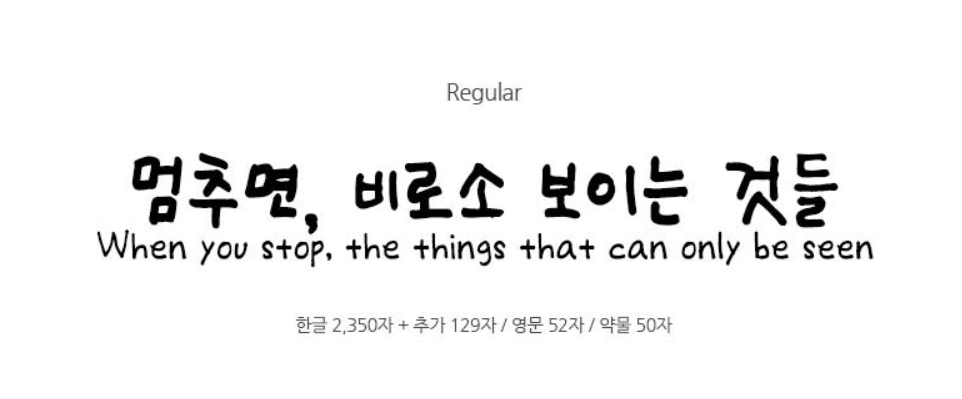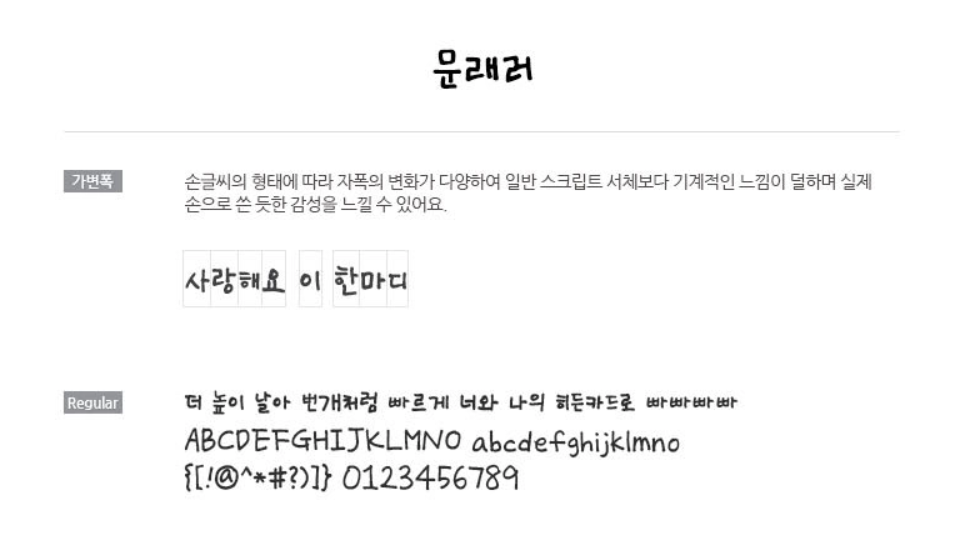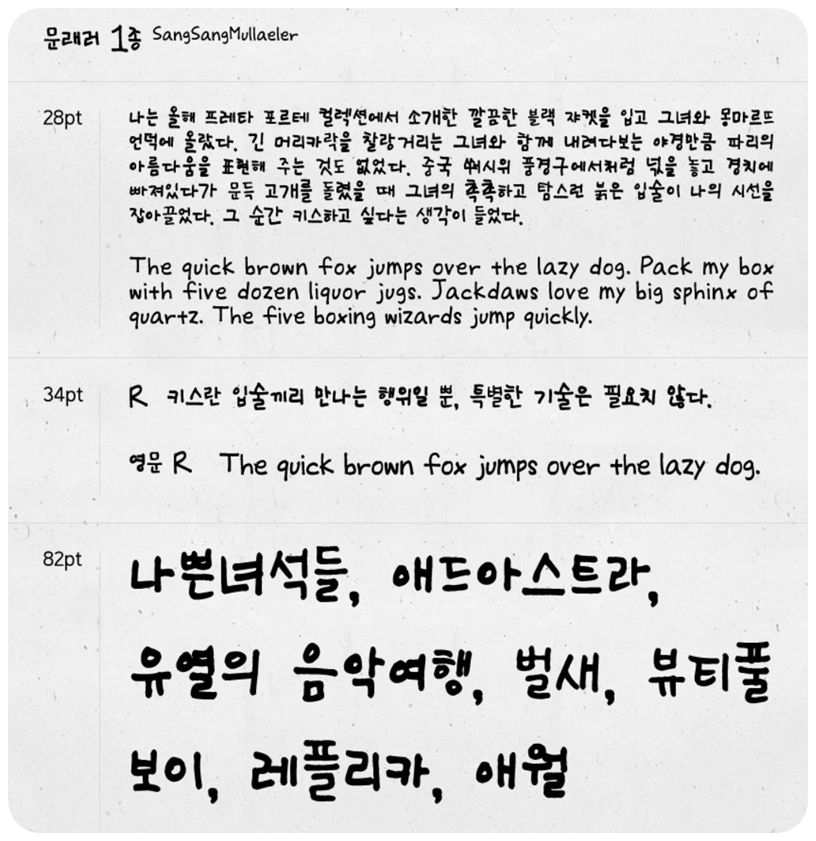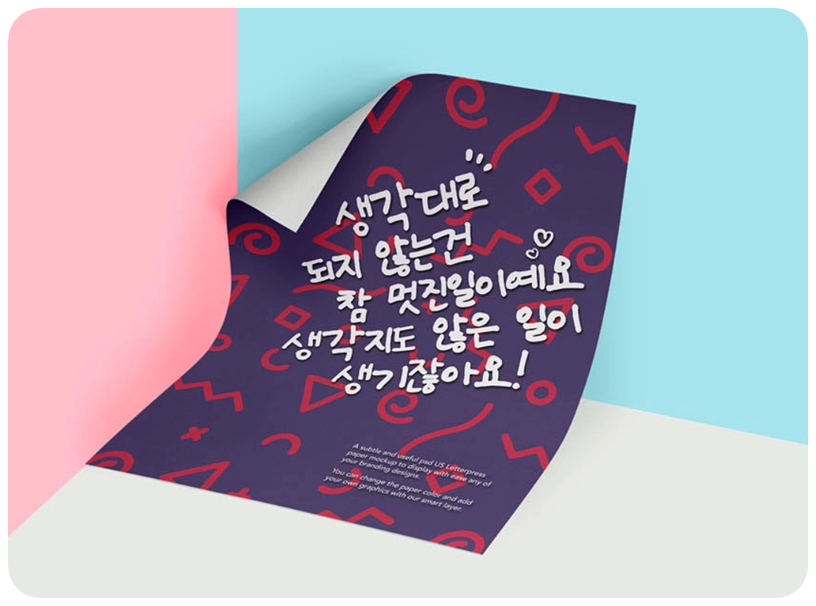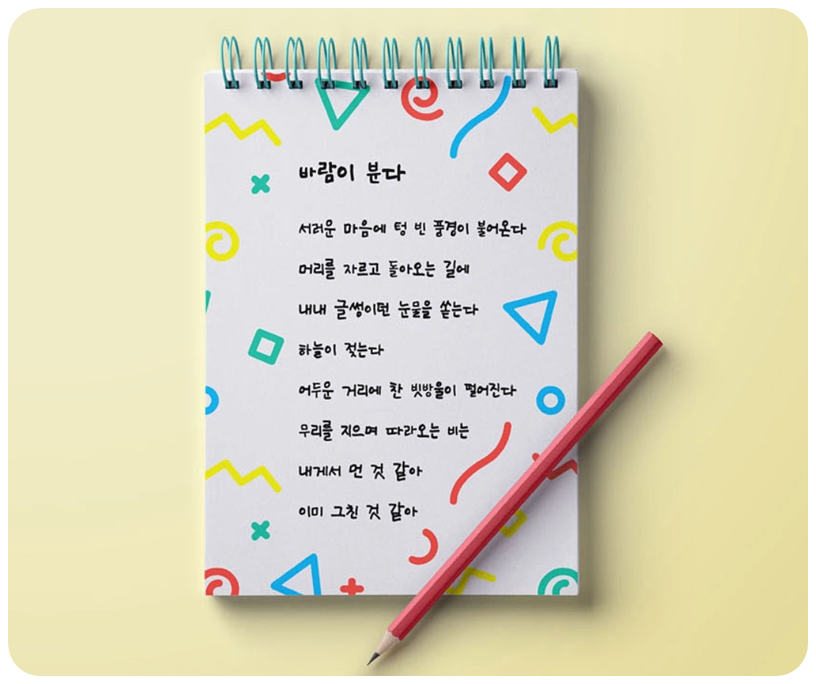
귀엽고 자연스러운 손글씨 폰트를 찾고 있다면 이 폰트를 주목해보세요.
문래동 감성을 그대로 담은 ‘문래러’ 폰트는 일상적인 글씨 느낌을 살린 매력적인 서체입니다.
문래러 폰트란?
‘문래러’는 상상토끼에서 제작한 감성 손글씨 폰트로, 문래동을 사랑하는 사용자의 실제 필체를 기반으로 만들어진 서체입니다.
일상에서 자연스럽게 쓰인 글씨를 그대로 살려, 꾸밈없이 편안한 느낌을 주는 것이 특징입니다.
폰트 특징
✔️ 실제 손글씨 기반 제작
✔️ 귀엽고 자연스러운 필기체 스타일
✔️ 꾸미지 않은 듯한 편안한 감성
✔️ 다양한 콘텐츠에 활용 가능한 디자인
특히 과하지 않은 개성 덕분에 블로그, SNS, 썸네일 등 어디에나 잘 어울리는 활용도 높은 폰트입니다.
활용 추천
📌 블로그 썸네일 및 SNS 콘텐츠
📌 카드뉴스 및 포스터 디자인
📌 유튜브 썸네일 및 자막
📌 감성 브랜딩 및 로고 디자인
자연스러운 필기체 느낌 덕분에 일상적인 감성을 살리고 싶은 콘텐츠에 특히 잘 어울립니다.
Q4. 어떤 콘텐츠에 잘 어울리나요?
블로그, SNS, 카드뉴스, 감성 디자인 콘텐츠 등에 잘 어울립니다.
문래러 폰트는 자연스러운 손글씨 감성과 실용성을 동시에 갖춘 무료 서체입니다.
꾸미지 않은 듯한 매력을 살린 디자인을 원한다면 꼭 활용해보세요.